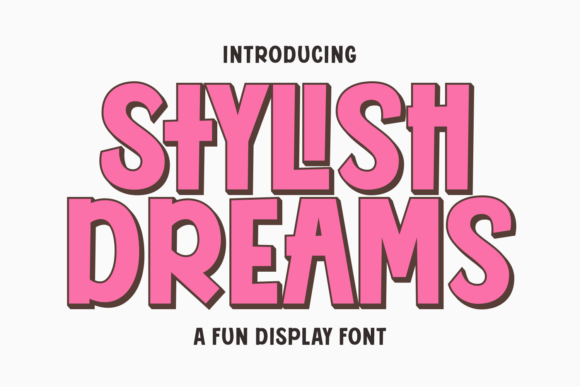
Stylish Dreams
Stylish Dreamsのような高品質の素材をお探しの場合、このプレミアムパッケージはクリエイティブなプロジェクトに素晴らしい選択です。
精密に作られたStylish Dreamsは、クリーンなベクター、滑らかなタイポグラフィ、そして安心のための商用ライセンスを提供します。